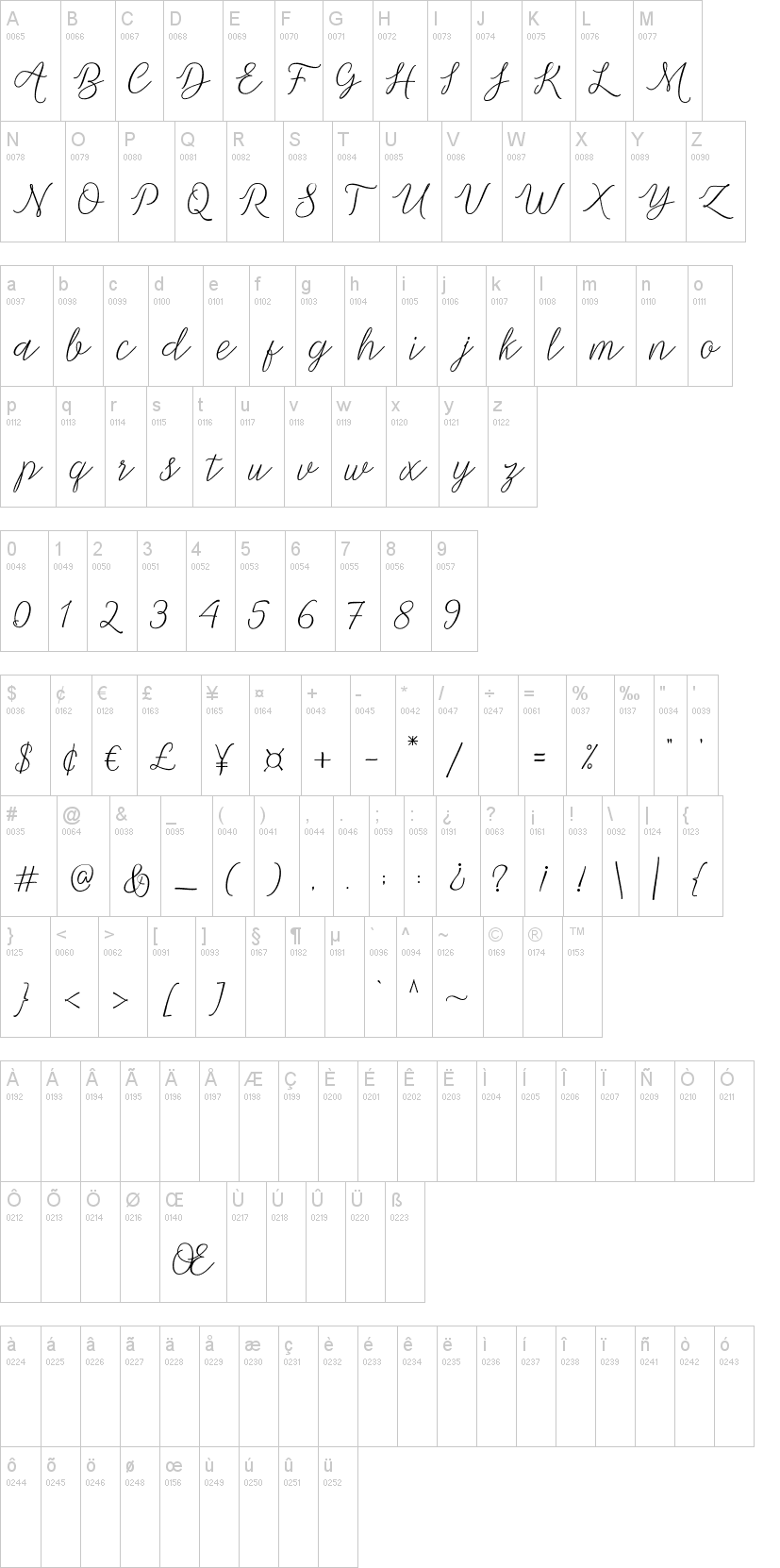
Michella是一种现代简约的字体,由设计师Michella设计,它结合了细节和宽松的线条,形成了一种明亮而又不失优雅的字体风格。它的字母形状是温柔而柔和的,字体的风格细腻且有节奏感,使它成为最适合用于报纸、杂志和网页的字体。此外,它还具有良好的可读性,可以用于许多类型的文本,从简短的标题到长篇文章。内容介绍
Michella是一款非常不错的手写艺术字体,具有很好的视觉感,适合于文化类的宣传设计、商业类品牌的广告和产品包装设计以及个性化文字排版等较多场景。